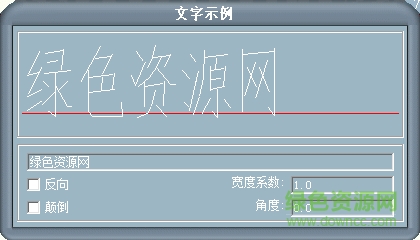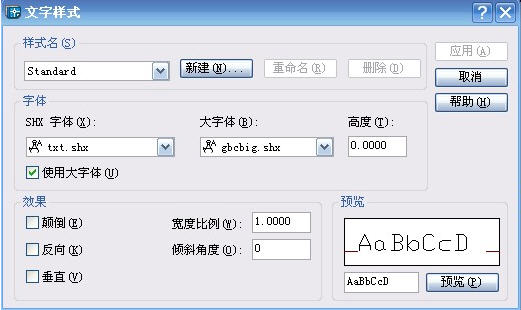
cad字體gbcbig.shx是autocad的一款大字體文件,字形偏大,筆畫細直,cad中使用挺多的,很多需要做圖紙的朋友可以使用這個字體,非常的不錯,需要的朋友,趕快來綠色資源網(wǎng)下載吧!
gbcbig.shx字體,這個字體是auto CAD軟件的大字體,在打開CAD圖紙的時候,有時會提示需要這種gbcbig.shx字體的選擇,如果沒有這個gbcbig.shx大字體的支持,那打開的DWG圖紙里的文字就會出現(xiàn)問號。